DNAを、手渡せるかたちへ
理念を日常へ運ぶ、触れられるブランド接点。
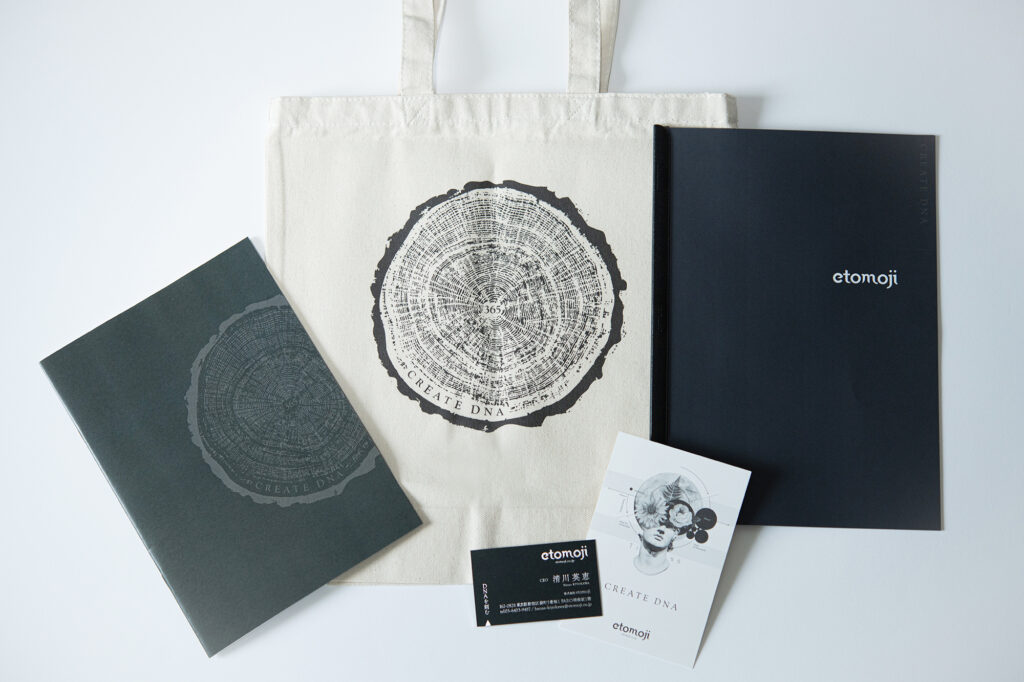
企業の理念やブランドメッセージを効果的に伝える手段として、オリジナルグッズの制作をいたしました。名刺をはじめ、トートバッグやノート、ステッカーなど様々なアイテムを制作しました。これらのグッズを通じて、私たちの理念を広く伝えることを目指しています。
グッズを通じて新たなコミュニケーションが生まれる重要性
グッズは単なるアイテムではなく、新たなコミュニケーション手法としての重要性を持っています。例えば、名刺は初対面の印象を残し、短くても的確なメッセージを伝えることができます。デザインや素材選びにこだわり、会社のブランドイメージを醸成することで、相手に深い印象を与えることができます。今回はそれらのアイテムについてお伝えをしていきます。
名刺: 初対面の印象を残し、理念を端的に伝えるツール
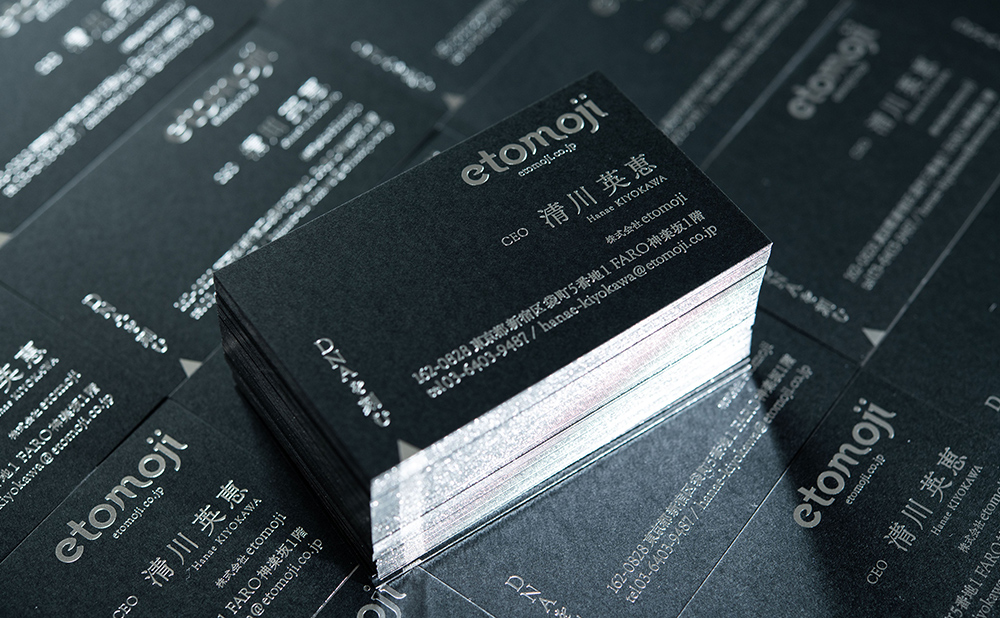
名刺は、分厚い400kgのケンランという紙を使って、表面には艶銀の箔押し、側面(紙厚部分)には天金加工を施しました。「DNAを刻む」と言うコンセプトに合わせて箔押しを選ぶことで、文字の細いところが刻まれたような表現になります。三角の切り欠きもポイントです。
名刺そのものの豪華さで、初対面の方からは必ず名刺に関するお言葉を頂戴します。最初の出会いの場だからこそ、コミュニケーションが広がるきっかけづくりをしたいですよね。
- デザインや素材選びにこだわり、会社のブランドイメージを醸成
- 簡潔なメッセージやキャッチフレーズを記載し、相手に印象を残す
トートバッグ: 持ち主のアイデンティティを反映し、理念を広めるアイテム
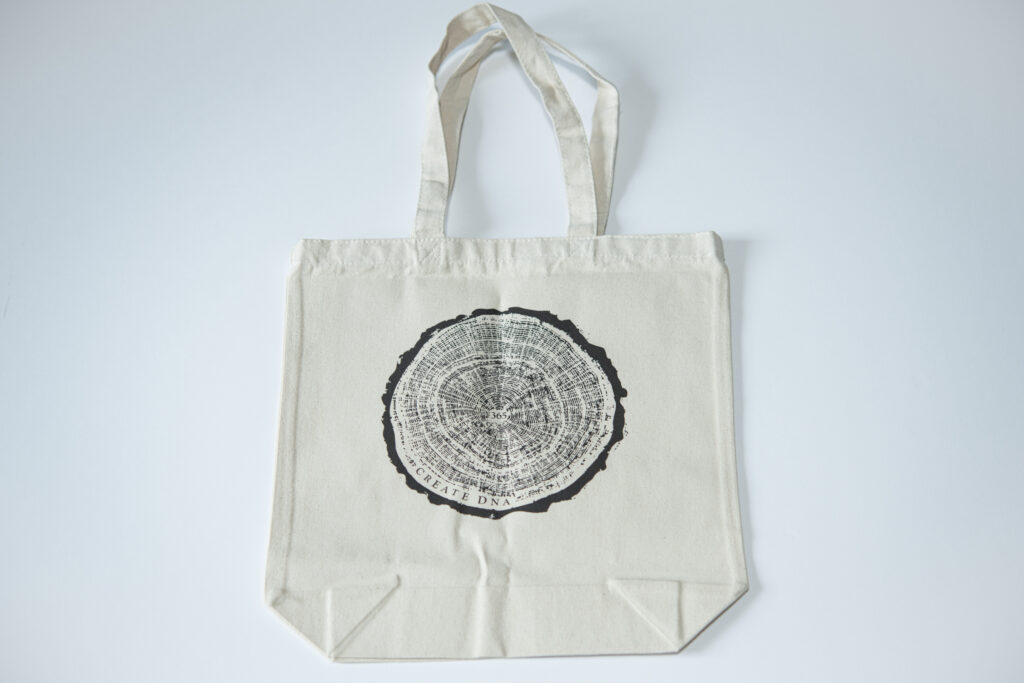
トートバッグは持ち主のアイデンティティを反映し、日常の様々なシーンで活躍します。使い勝手の良さとデザイン性を兼ね備えながら、大胆に理念やブランドメッセージをプリントすることで、周囲にアピールする効果があります。
「CREATE DNA」というフレーズを掲げ、木の年輪をイメージしたロゴを作成しました。毎日DNAを刻むという想いと覚悟から、中心には365(365日、毎日)を意味する文字を入れています。
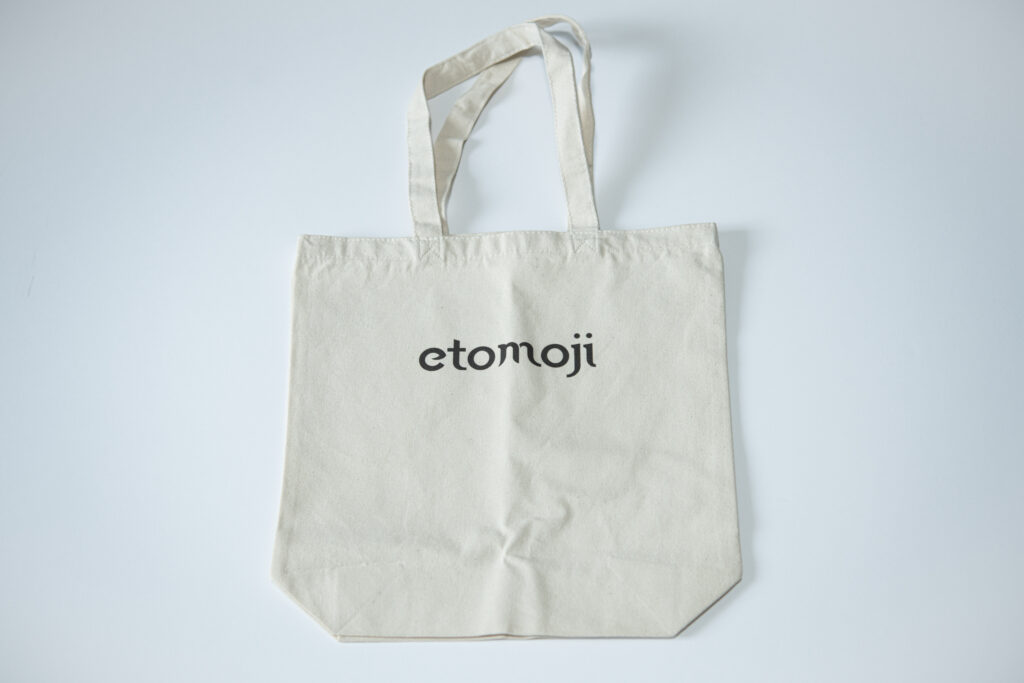
もう片方の面は、etomojiのロゴを入れています。シンプルですが、ロゴそのものの意味もあるので、欠かせないデザインです。実はetomojiのコーポレートロゴは最近マイナーチェンジを行いました。詳しくはまた別の記事でご紹介できればと思います。
- 使い勝手の良さとデザイン性を兼ね備え、日常の様々なシーンで活躍
- 理念やブランドメッセージをプリントし、周囲にアピール
ノート: 継続的なコミュニケーションを促し、理念を浸透させる道具
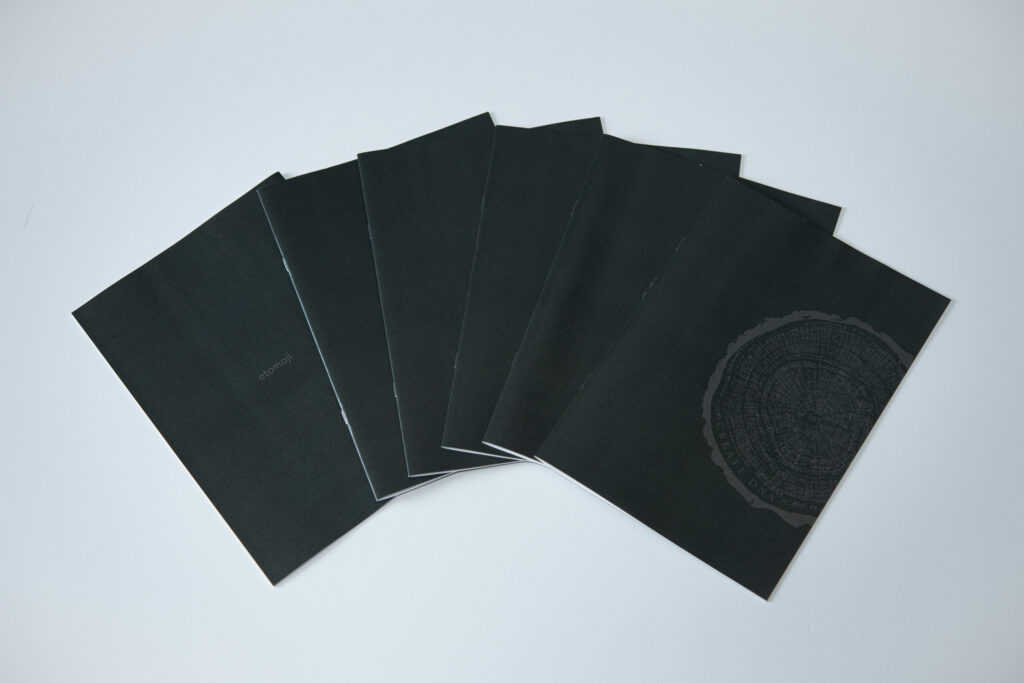
ノートは継続的なコミュニケーションを促し、理念を浸透させる道具として活用されます。会議や打ち合わせの際に使用され、カバーデザインやページには企業のビジョンや価値観が掲載され、ユーザーに共感を呼び起こします。ノートはメモやアイデアを書き込む場として存在感を示すだけでなく、企業とのつながりを感じさせる重要なアイテムです。
- 経営者が理念を考えるきっかけとして、継続的な思考の時間を提供し、理念の言語化に
- 会議や打ち合わせ時に活用され、メモやアイデアを書き込む場として便利
ステッカー: 視認性の高い小さな広告媒体としての役割を果たす
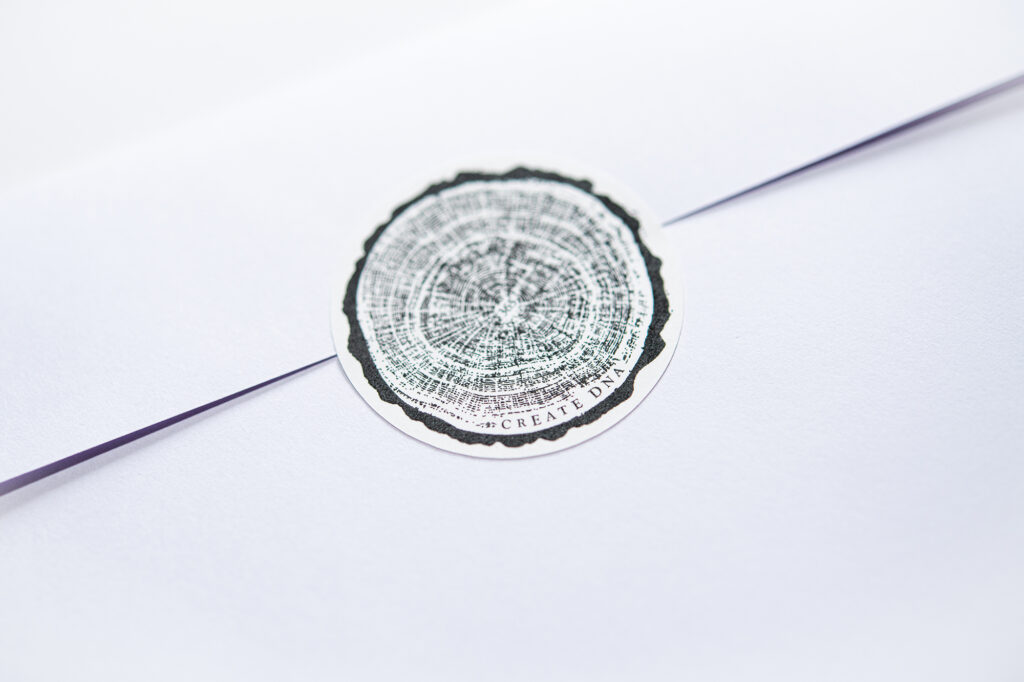
ステッカーは小さな広告媒体としての役割を果たします。小さなサイズでも様々なところに貼られることで、人目に触れることになります。特に、デザインやメッセージが鮮明で、人々の目を引くようなステッカーは、会社の理念を広める上で強力なツールとなります。
- ワンポイントに象徴となるロゴやメッセージを刻むことで価値観を浸透させる
お客様の目に触れることで理念の浸透を促すことは立派なブランディング活動のひとつ